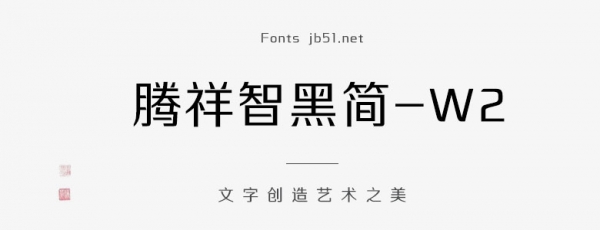
騰祥智黑簡-W2是一款不錯(cuò)的藝術(shù)字體,由騰祥字庫出品,這款字體屬于騰祥智黑系列字庫,該系列一共有六款粗細(xì),以W1至W6命名,這款字體是智黑系列中較細(xì)一款,適合應(yīng)用于藝術(shù)設(shè)計(jì)、平面宣傳設(shè)計(jì)、網(wǎng)頁設(shè)計(jì),書法字帖等領(lǐng)域,需要的朋友可以前來本站下載。
騰祥智黑系列字庫是騰祥睿黑系列字庫的兄弟篇,與睿黑風(fēng)格相近但排版效果迥異。該系列一共有六款粗細(xì),以W1至W6命名。智黑系列更強(qiáng)調(diào)了黑體的特征,筆畫簡潔、硬朗、穩(wěn)重大方。塔形頓點(diǎn)、撇點(diǎn)賦予了智黑特殊的設(shè)計(jì)效果,使智黑又區(qū)別于傳統(tǒng)的黑體,既具有黑體的魅力又具有一定的裝飾特色,使黑體具有了靈活、生動(dòng)的特點(diǎn),從而形成自己鮮明的特色。本款字庫為智黑系列中較細(xì)一款W2,筆畫精致、簡潔清晰,適用于正文、屏顯、設(shè)計(jì)類用字。比通常的宋體、黑體正文字體有更好的版面效果。